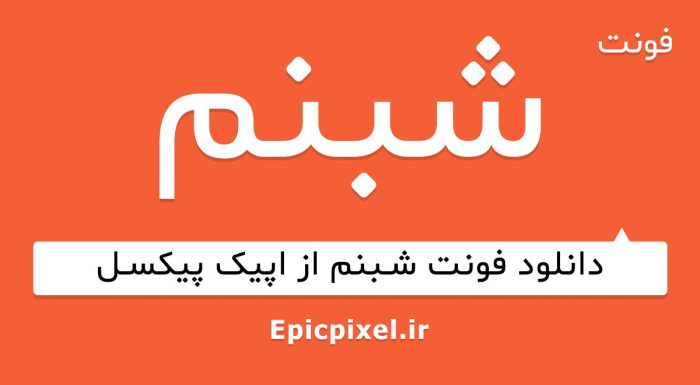
12 فونت شبنم فارسی
فونت شبنم زیبایی ظرافت در طراحی گرافیک فارسی
فونت شبنم یکی از فونتهای باکیفیت و محبوب در دنیای طراحی گرافیک فارسی است که به دلیل زیبایی و خوانایی چشمگیرش، در بین طراحان و کاربران بسیار مورد توجه قرار گرفته است. این فونت بهخوبی توانسته است نیاز به یک جایگزین برای فونت یکان را برطرف کند و به یکی از پرکاربردترین فونتهای فارسی تبدیل شود. در این مقاله قصد داریم به معرفی فونت شبنم، ویژگیها و کاربردهای آن بپردازیم.
ریشههای فونت شبنم
فونت شبنم توسط صابر راستی کردار، هنرمند و طراح گرافیک ایرانی، طراحی شده است. این فونت بر اساس فونت وزیر که خود از فونت DejaVu بازطراحی شده است، خلق شده است. در طراحی فونت شبنم، از فونت یکان نیز الهام گرفته شده است، بنابراین این فونت ترکیبی از زیبایی و خوانایی هر دو فونت را در خود دارد.
ویژگیهای فونت شبنم
فونت شبنم دارای ویژگیهای منحصر به فردی است که باعث شده است به یکی از فونتهای محبوب در میان طراحان و کاربران فارسی زبان تبدیل شود. از جمله این ویژگیها میتوان به موارد زیر اشاره کرد:
دانلودخوانایی بالا: فونت شبنم به دلیل قلمهای ظریف و منظم خود، خوانایی بسیار بالایی دارد و به راحتی قابل خواندن است. این ویژگی باعث شده است که این فونت برای استفاده در متون طولانی و نوشتههای رسمی بسیار مناسب باشد.
زیبایی بصری: فونت شبنم دارای ظاهری زیبا و چشم نواز است و به خوبی با سبکهای مختلف طراحی گرافیک فارسی هماهنگ میشود. این فونت برای استفاده در پوسترهای تبلیغاتی، طراحی وب، طراحی صفحات کتاب و مجلات و بسیاری دیگر از موارد بسیار مناسب است.
تنوع وزنها: فونت شبنم در پنج وزن مختلف از نازک تا ضخیم ارائه شده است که این امکان را به طراحان میدهد تا در هر پروژهای، وزن مناسب را انتخاب کنند.
کاربردهای فونت شبنم
فونت شبنم به دلیل ویژگیهای منحصر به فرد خود، در بسیاری از زمینههای مختلف کاربرد دارد. از جمله کاربردهای این فونت میتوان به موارد زیر اشاره کرد:
طراحی صفحات وب: فونت شبنم به دلیل خوانایی بالای خود، برای استفاده در طراحی صفحات وب بسیار مناسب است. این فونت میتواند برای عنوانها، متنهای طولانی و سایر عناصر بصری وب سایت مورد استفاده قرار گیرد.
طراحی پوسترها و تراکتهای تبلیغاتی: فونت شبنم به دلیل زیبایی بصری خود، برای طراحی پوسترها و تراکتهای تبلیغاتی بسیار مناسب است. این فونت میتواند برای برجسته کردن پیام تبلیغاتی و جلب توجه مخاطبان استفاده شود.
طراحی صفحات کتاب و مجلات: فونت شبنم به دلیل خوانایی بالای خود، برای استفاده در طراحی صفحات کتاب و مجلات بسیار مناسب است. این فونت میتواند برای متن اصلی کتاب یا مجله و همچنین برای عنوانها، سرفصلها و سایر عناصر بصری استفاده شود.
طراحی گرافیک رومیزی: فونت شبنم برای استفاده در طراحی گرافیک رومیزی مانند طراحی کارت ویزیت، پاکت نامه و سایر قطعات چاپی نیز بسیار مناسب است.
نتیجهگیری
فونت شبنم یکی از فونتهای محبوب و پرکاربرد در دنیای طراحی گرافیک فارسی است. این فونت به دلیل ویژگیهای منحصر به فرد خود، مانند خوانایی بالا، زیبایی بصری و تنوع وزنها، برای استفاده در بسیاری از زمینههای مختلف مناسب است. اگر به دنبال یک فونت فارسی زیبا و خوانا هستید، فونت شبنم یکی از بهترین گزینههای موجود است.
فونت شبنم در چه وزنهایی ارائه شده است؟
فونت شبنم در پنج وزن مختلف از نازک تا ضخیم ارائه شده است:
نازک (Thin)
سبک (Light)
معمولی (Regular)
متوسط (Medium)
ضخیم (Bold)
آیا فونت شبنم با همه نرم افزارهای طراحی گرافیک سازگار است؟
بله، فونت شبنم با بسیاری از نرم افزارهای طراحی گرافیک سازگار است، از جمله:
Adobe Photoshop
Adobe Illustrator
CorelDRAW
GIMP
Inkscape
بهترین وزن فونت شبنم برای استفاده در صفحات وب کدام است؟
بهترین وزن فونت شبنم برای استفاده در صفحات وب، وزن معمولی (Regular) است. این وزن خوانایی بالایی دارد و به راحتی قابل خواندن است.
البته، پاسخ به این سوالات تا حدی به نیازها و سلیقه شما بستگی دارد. برای مثال، اگر به دنبال یک فونت نازک و ظریف برای استفاده در پوسترهای تبلیغاتی هستید، وزن نازک (Thin) میتواند گزینه مناسبی برای شما باشد.
در اینجا چند نکته برای استفاده موثر از فونت شبنم ارائه شده است:
برای استفاده در متنهای طولانی، از وزنهای معمولی (Regular) یا سبک (Light) استفاده کنید.
برای استفاده در عنوانها و سرفصلها، از وزنهای متوسط (Medium) یا ضخیم (Bold) استفاده کنید.
برای استفاده در طراحی صفحات وب، از وزنهای معمولی (Regular) یا نازک (Thin) استفاده کنید.
با رعایت این نکات، میتوانید از فونت شبنم به بهترین شکل ممکن استفاده کنید و طراحیهای زیبایی را خلق کنید.